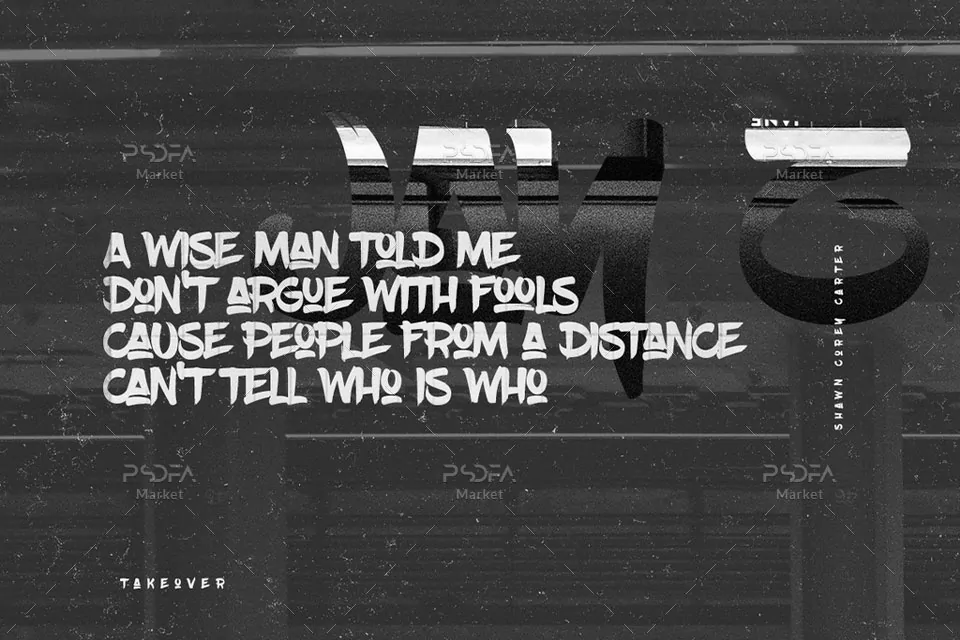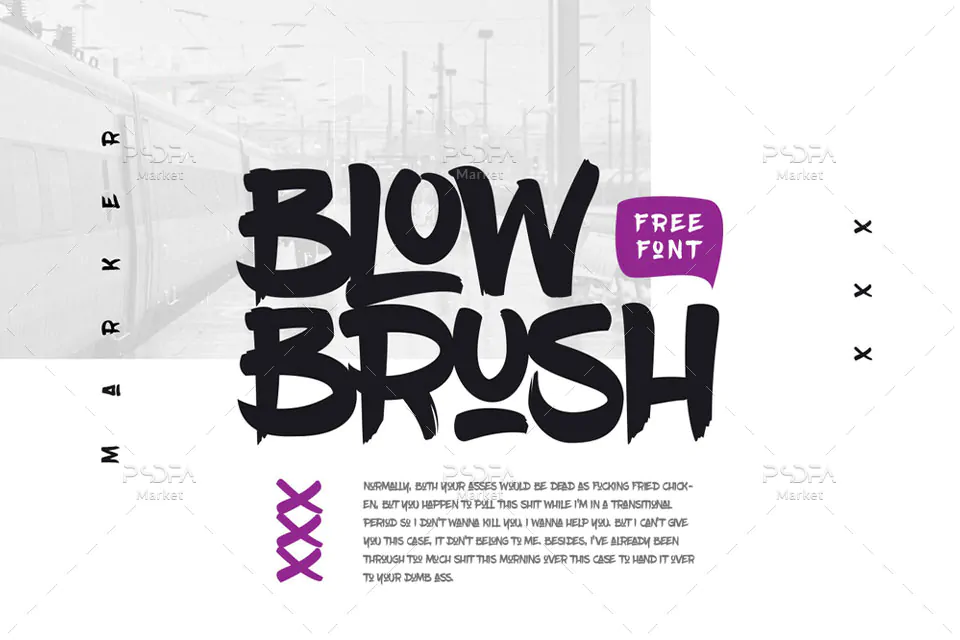
فونت انگلیسی زیبا و جذاب BlowBrush
فونت انگلیسی زیبا و جذاب
فونت فوق العاده زیبا و جذاب BlowBrush یکی دیگر از فونت های زیبای انگلیسی می باشد که می تواند به طرح های شما زیبایی خاصی بخشد . این فونت که فرمت آن OTF است دارای شکل نامنظم و استایل قلموی پر رنگ می باشد . پیش نمایش این فونت زیبا را می توانید در تصاویر زیر مشاهده فرمائید.